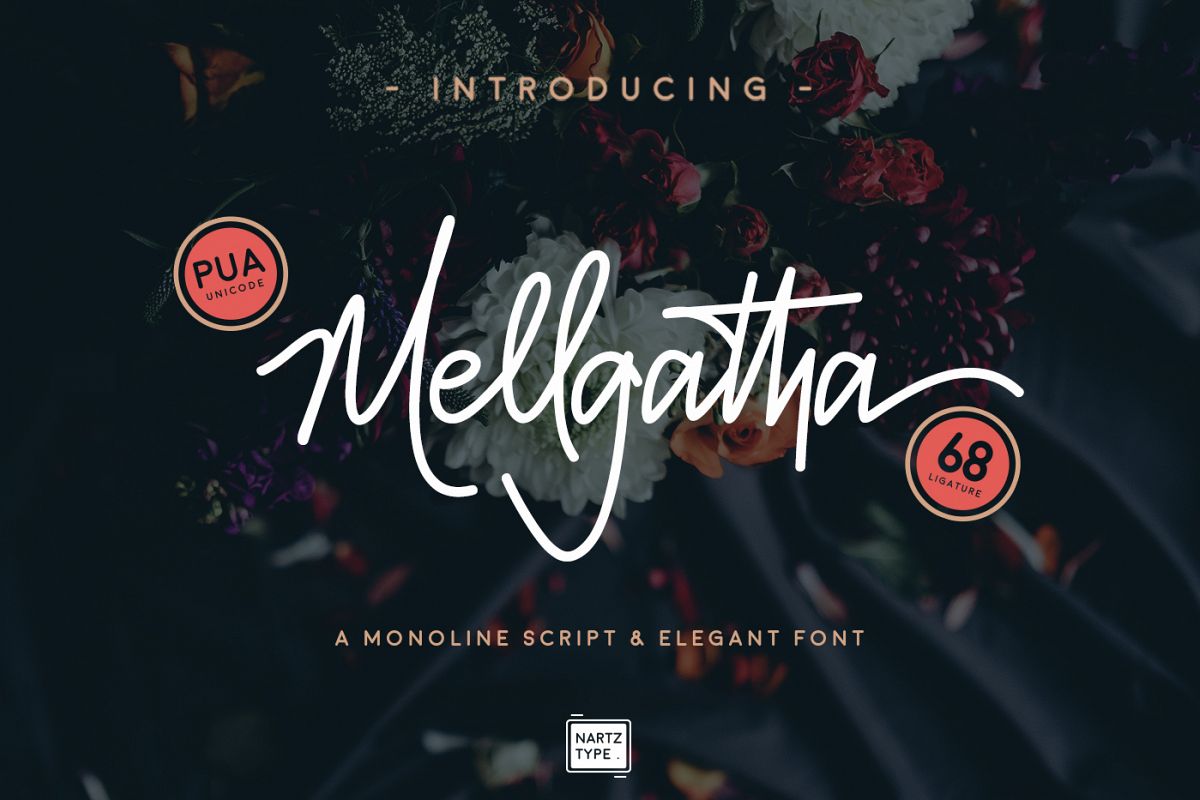
Mellgatha Monoline Script dengan  bangga mempersembahkan adalah font font elegan terbaru dan paling menakjubkan, dirancang untuk membuat tipografi atau huruf yang indah, Terlihat cantik saat digunakan untuk logo pribadi dan kop surat. Merek, majalah, kartu nama, undangan pernikahan, spanduk promosi, dan apa pun yang Anda inginkan.
Mellgatha Monoline Script juga mencakup set lengkap huruf besar dan kecil, simbol multibahasa, angka, tanda baca. Font telah, jadi itu akan sempurna untuk semua jenis teknik pencetakan, Anda dapat melakukan bordir, pemotongan laser, foil emas, kemeja cetak tradisional atau apa pun yang Anda ingin cetak. Mellgatha Monoline Script sangat mudah digunakan, cukup tulis nama teks, logo, atau apa pun yang Anda inginkan!
multibahasa -Alternate Huruf kecil -Ligatur
Khusus